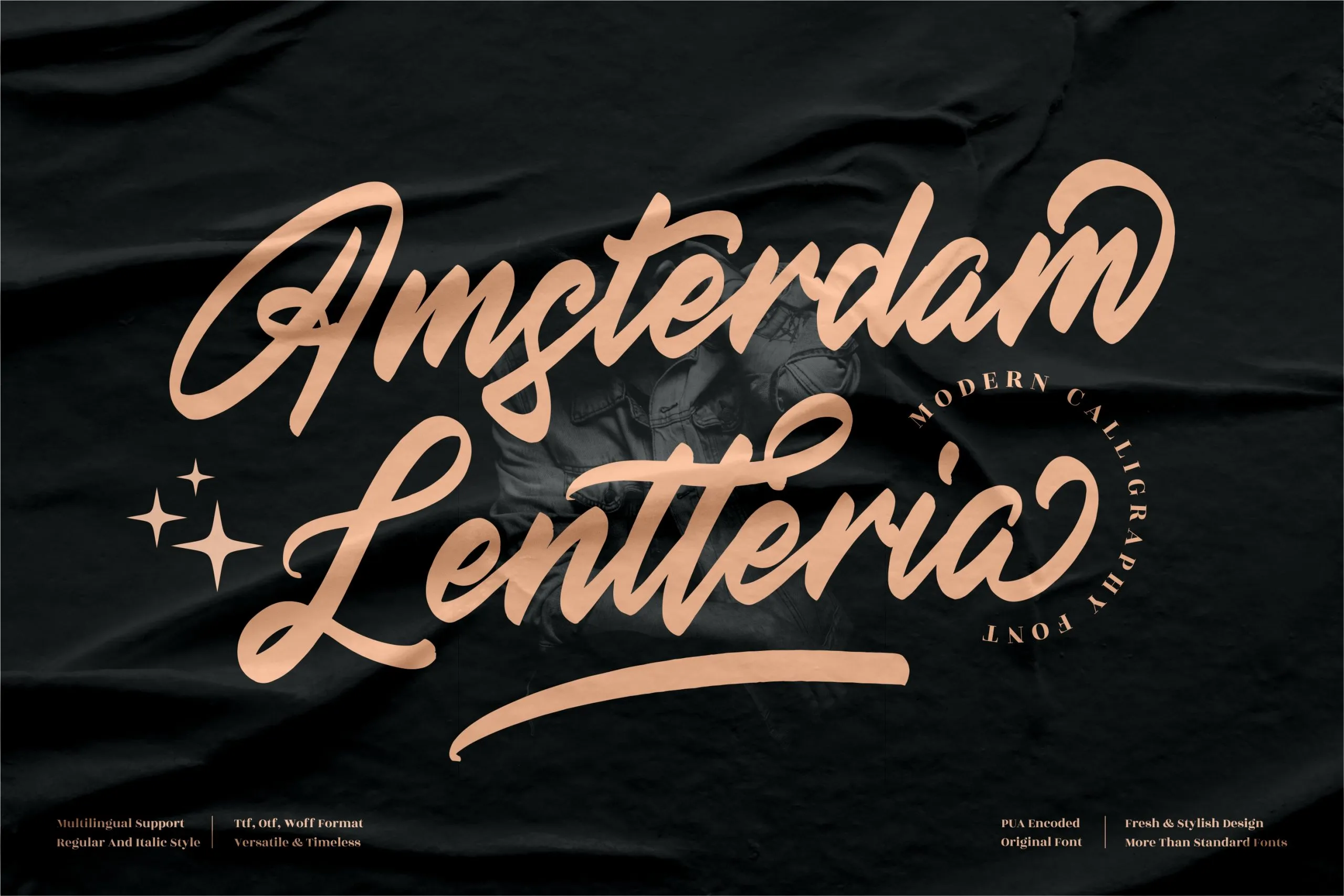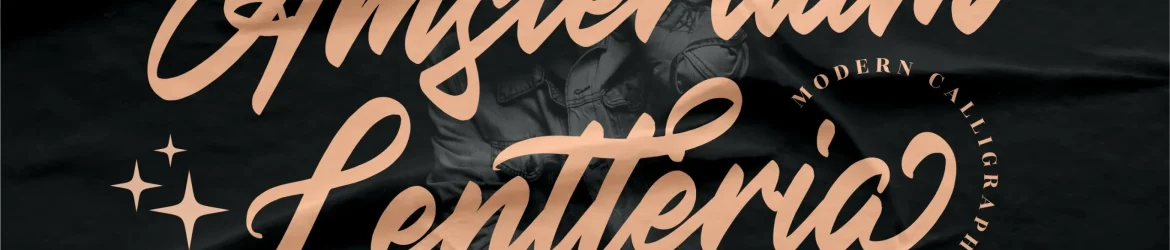
A Amsterdam Lentteria Font é uma elegante escolha para qualquer projeto que exige um toque sofisticado e sofisticado. Desenvolvida por perspectype, esta fonte script está perfeitamente projetada para dar vida à suas criações de design em alta qualidade. Seja para criar marcas de marca memoráveis, etiquetas gourmet ou até mesmo capas de livros com ares refinados, essa fonte certamente fará o seu trabalho. Se você estiver procurando por uma fonte que possa dar um toque especial às suas criações e fazer com que elas se destaquem, a Amsterdam Lentteria Font é definitivamente para você. Com uma ampla gama de aplicabilidades, seja em projetos digitais ou impressos, essa fonte atende a todos os requisitos de design que exigem um toque de luxo e sofisticação. Não importa qual projeto você está trabalhando, com a Amsterdam Lentteria Font, pode garantir uma assinatura única e elegante em seu trabalho.